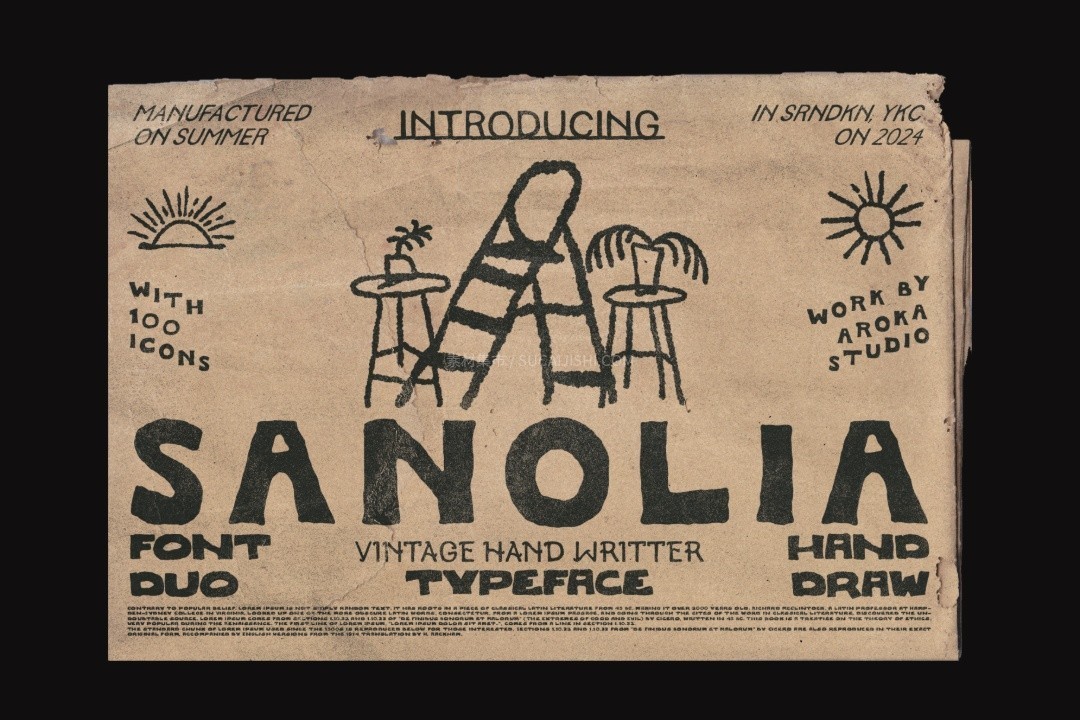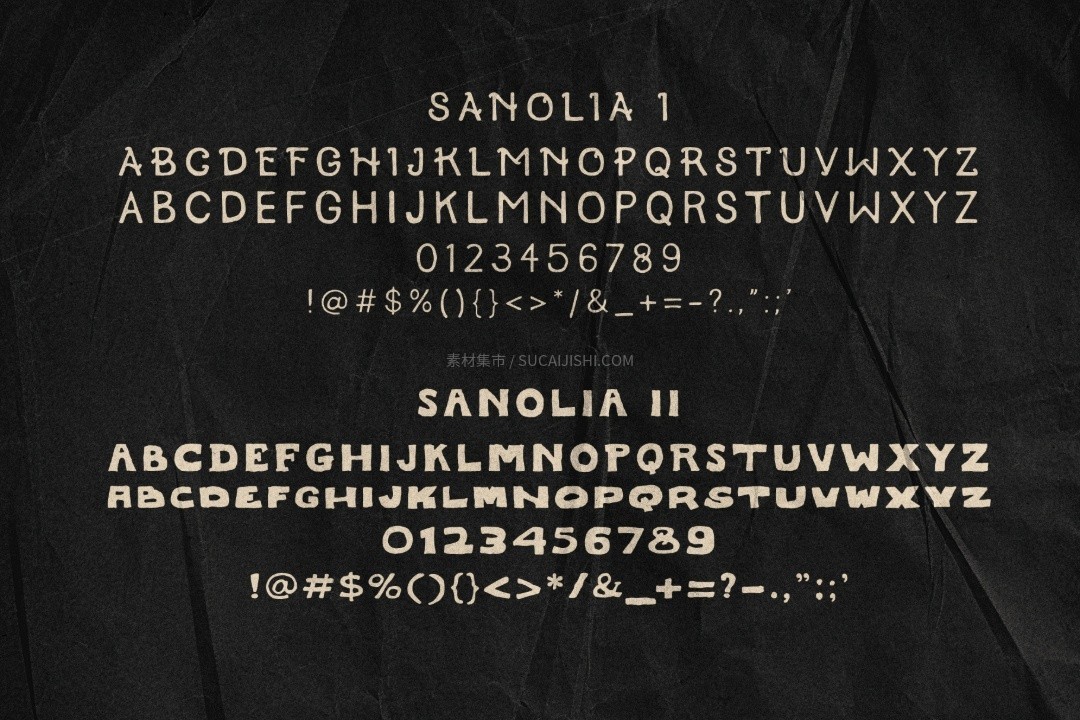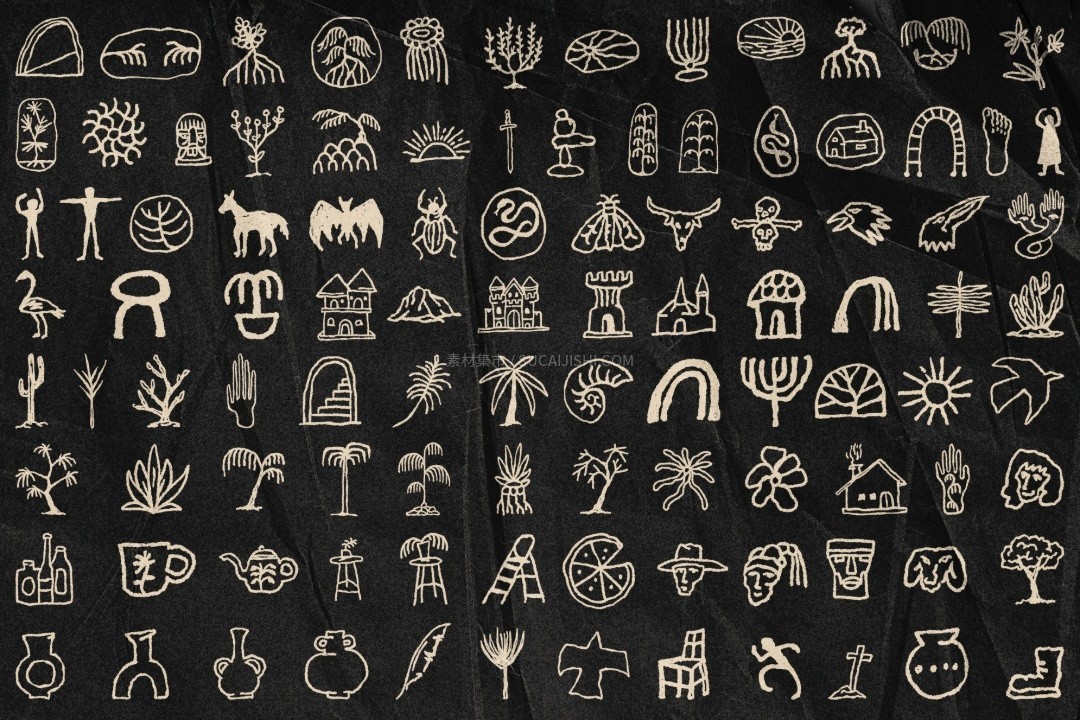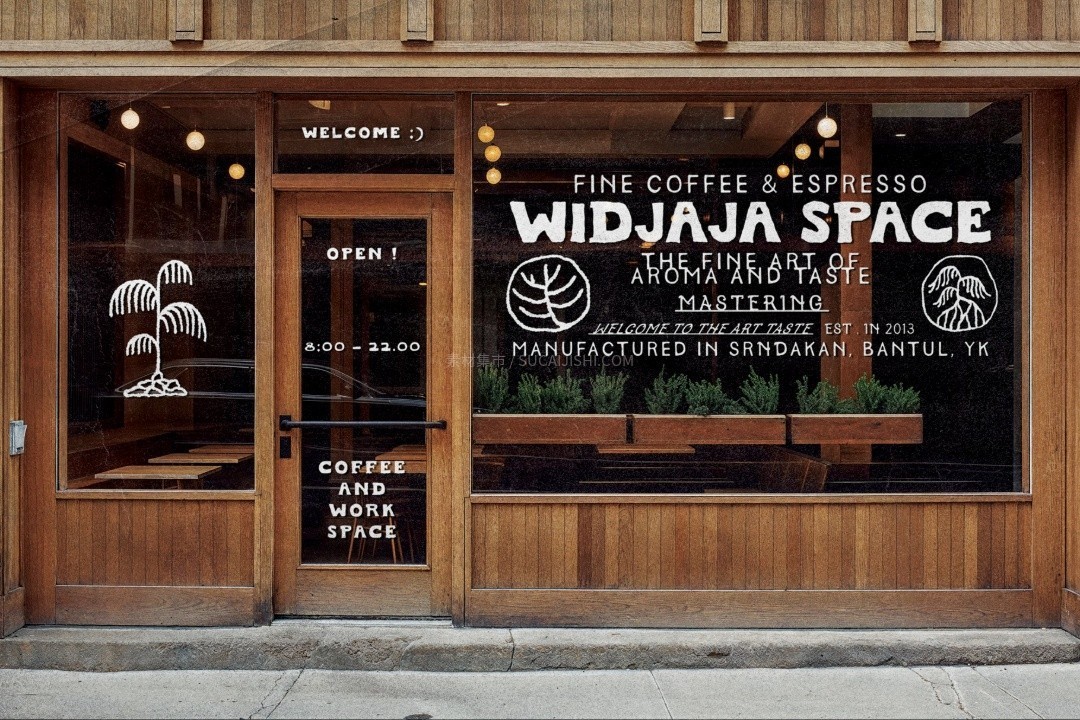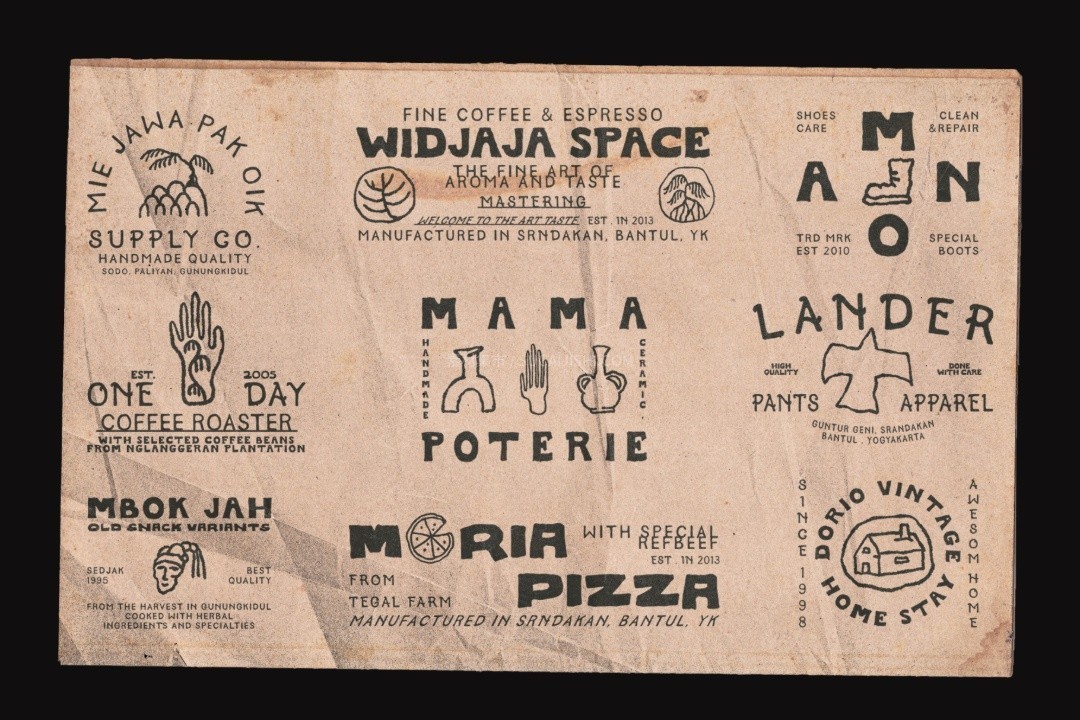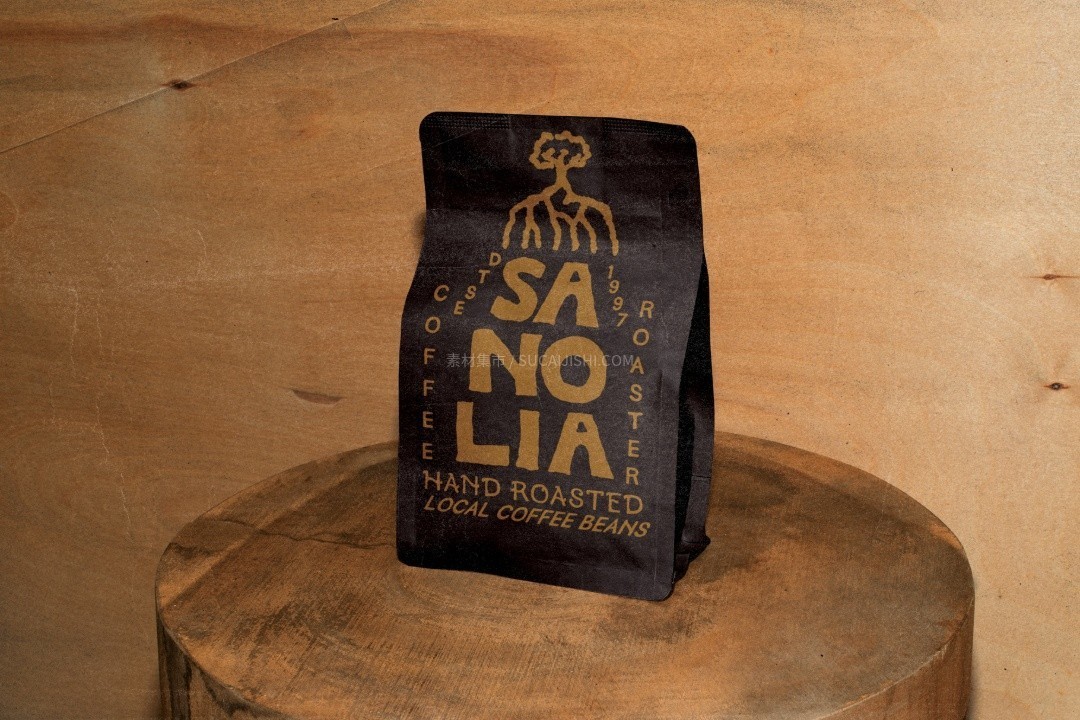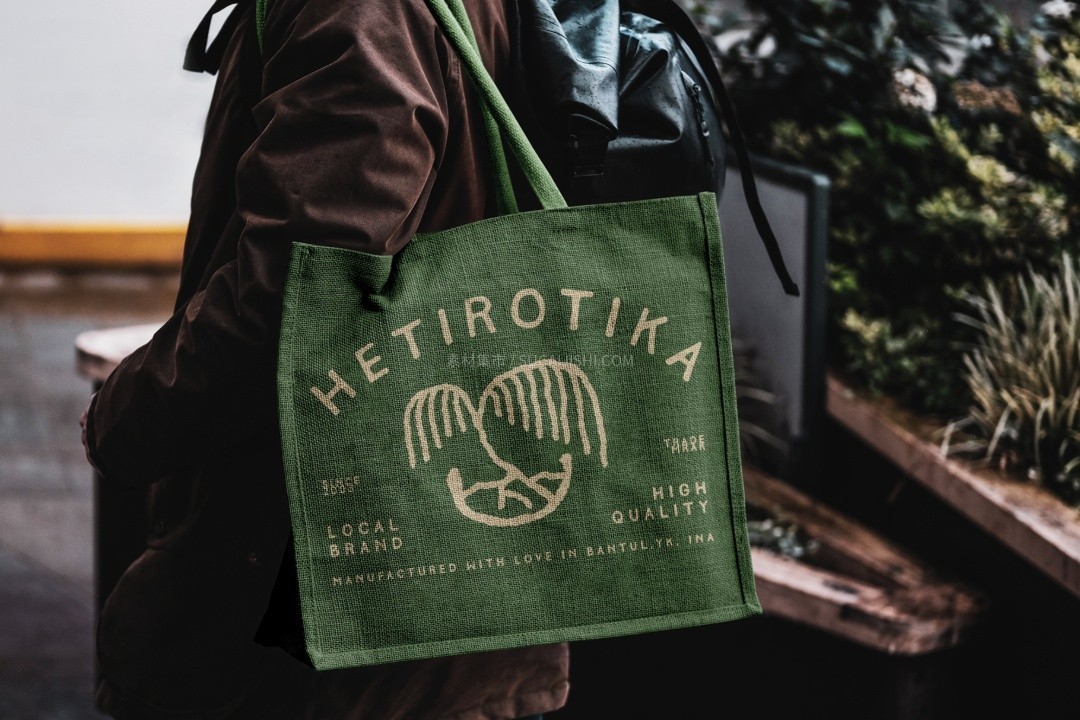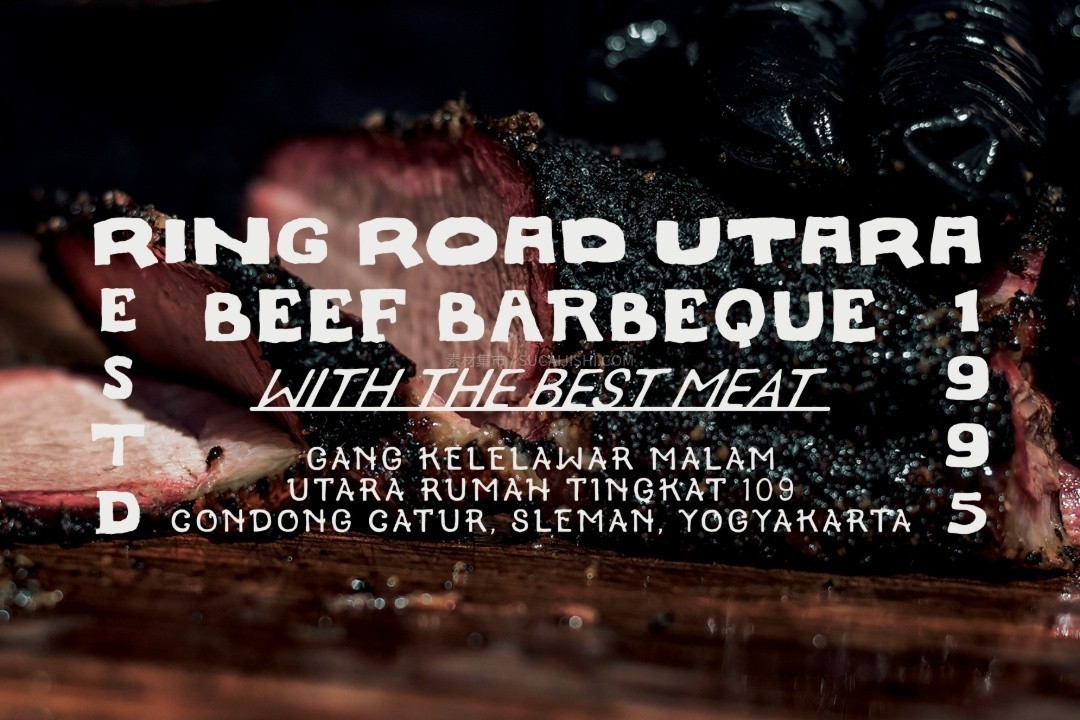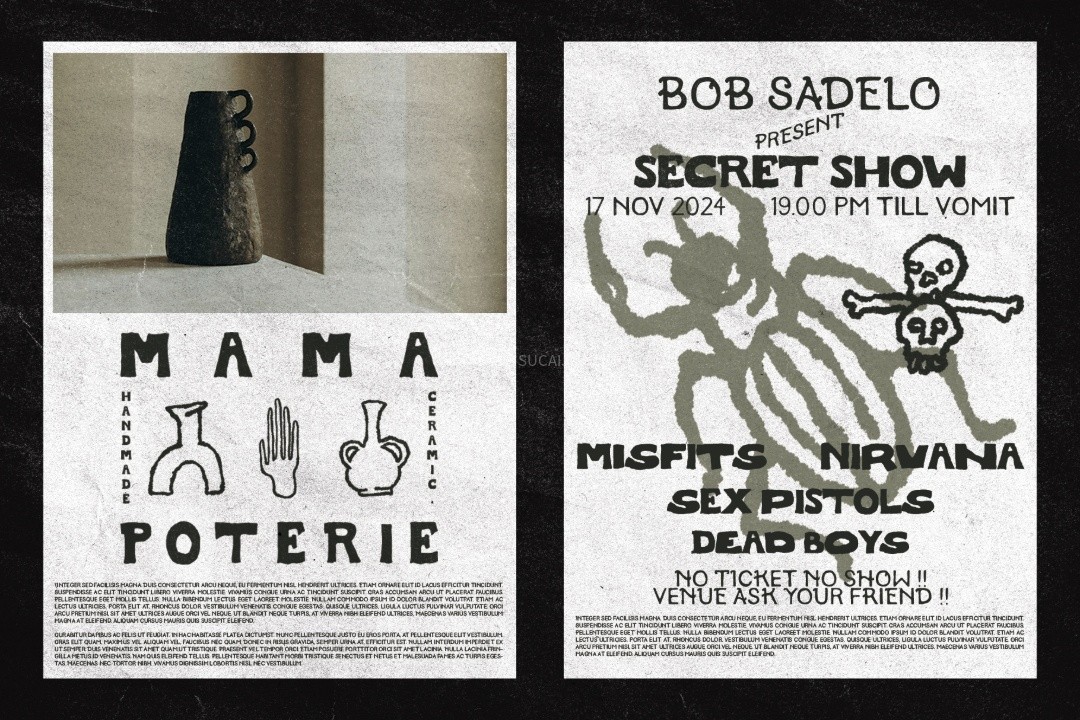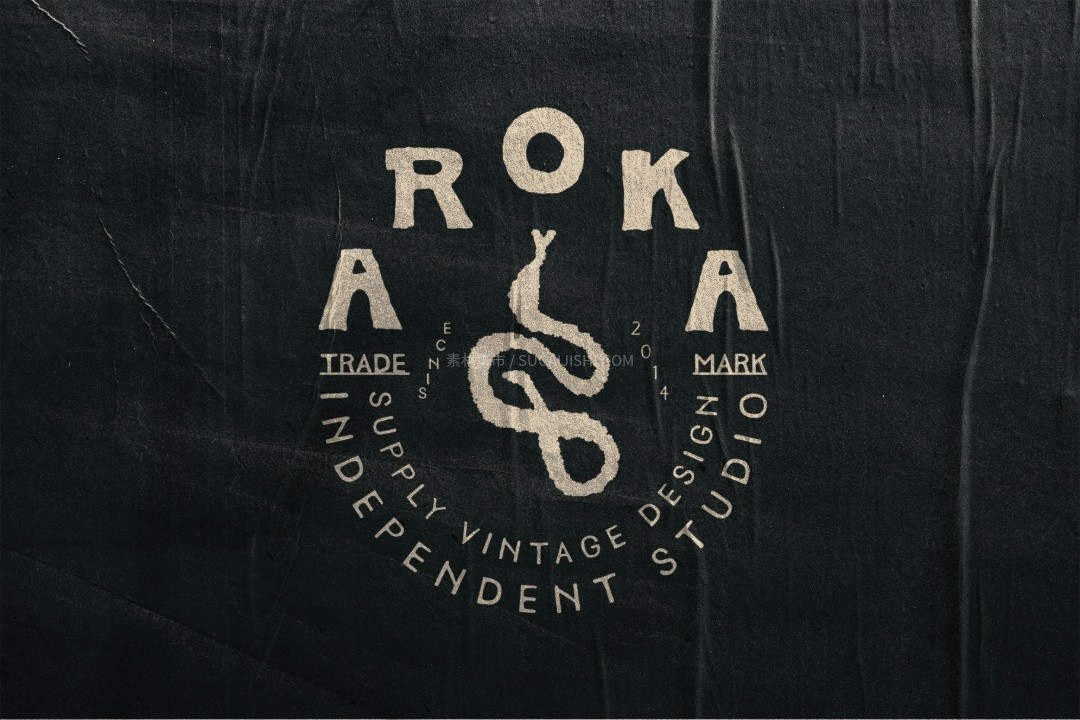
SANOLIA复古野趣风英文手绘字体+矢量装饰图形
一套非常有味道的复古手写字体组合——SANOLIA。它不仅包含两款搭配得恰到好处的英文字体(提供2个OTF文件),除了字体本身,套装里还一口气打包了100个PNG免抠图片和100个SVG矢量图形,甚至连Ai源文件都给你准备好了。做复古风排版、品牌视觉或者文创周边时,直接把手写字和这些图形素材拼合在一起,那种自然又随性的手绘复古感瞬间拉满,排版出效果特别快。